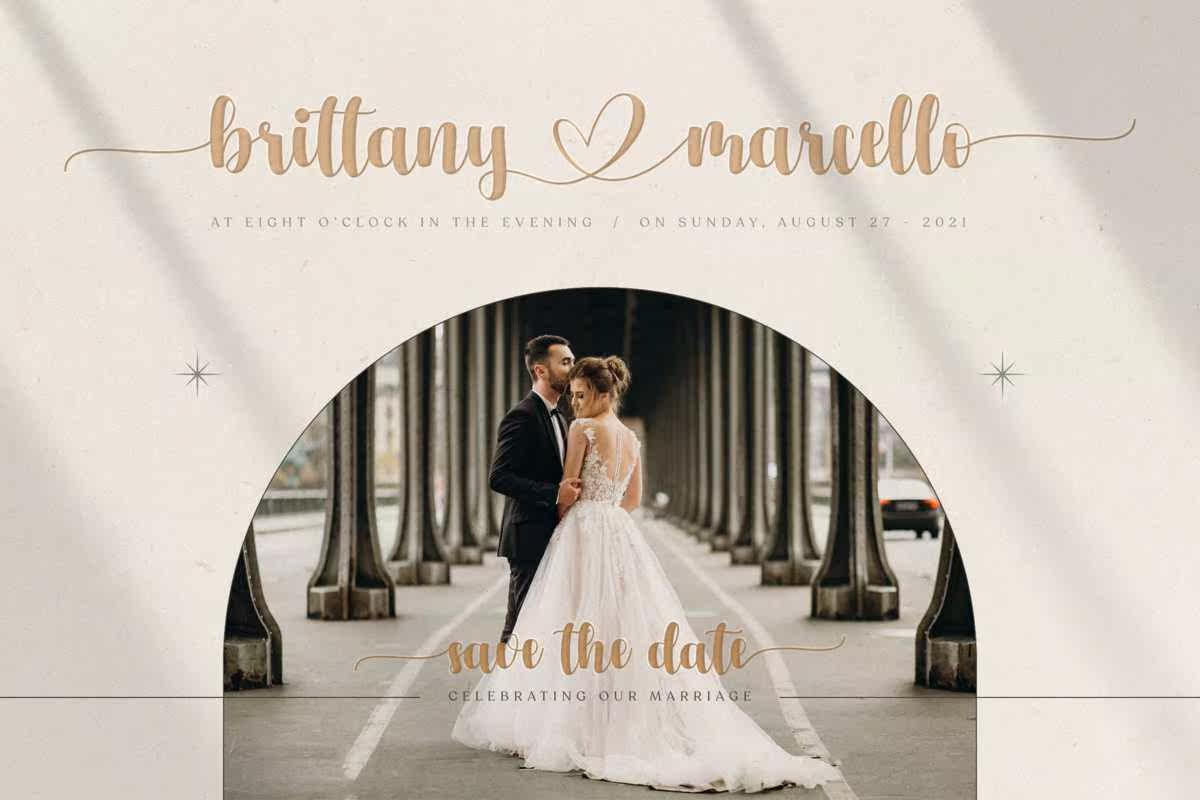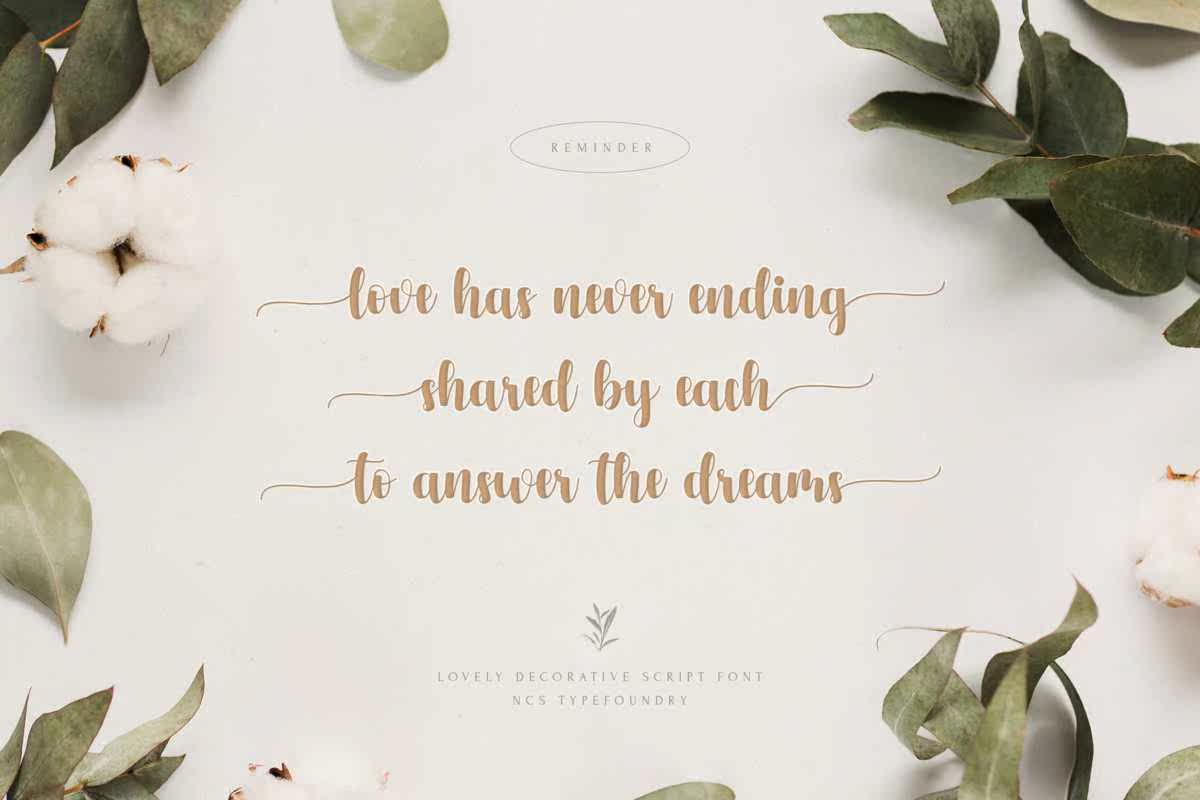
BoldDecorativeScriptFont具有现代感和书写感,温馨、浪漫、愉悦,此Font将使您的每一个项目都成为艺术作品。完美结合了活力、徽标、品牌、包装以及可编辑设计。自然风格的手写体美化和美学Font让您的非凡项目更加完美。BoldDecorativeScriptFont具有现代感和书写感,温馨,浪漫而愉快的是,此字体将使您的每一个项目都成为艺术作品。完美地结合了活力、徽标、品牌、包装以及可裁剪设计。自然风格的手写体美丽而美观的字体将完善您非凡的项目。